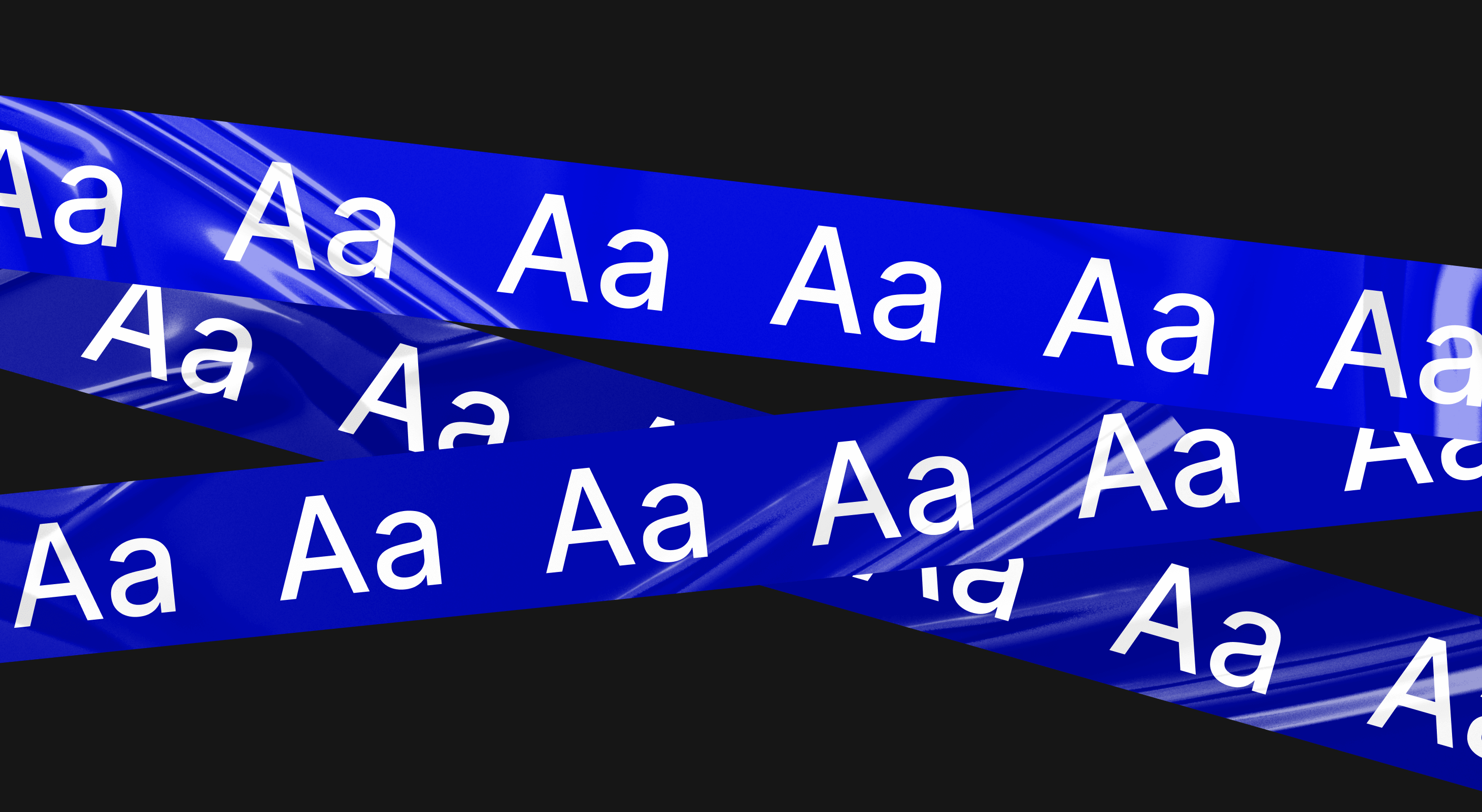
Как создать свой шрифт: инструкция
Если вы занимаетесь дизайном, но ни один из существующих шрифтов не подходит для вашего проекта, то создайте его сами. Это большой проект, но потраченные время и силы оправдают себя. В материале вместе с дизайнером Дарьей Токаревой разбираемся, как разработать и оцифровать свой шрифт.
Что нужно для создания шрифта
Чтобы сделать шрифт, нам нужно понимать, что же он из себя представляет. Крайне важно ориентироваться в базе типографики и разбираться в ее разновидностях. Это поможет определиться с целеполаганием: для чего создаем и где будем использовать.
Шрифт — набор графических знаков, который используется для отображения и восприятия текста. Каркас буквы — графема, которая служит базой для любого шрифта. По графеме мы понимаем, какая перед нами буква: к примеру, Н отличается от Л и О в любом шрифте и начертании.
Графема
Пример графем. Источник
Основные типы шрифтов:
1. Гротеск — шрифт без маленьких линий на концах штрихов, проще говоря, без засечек. Буквы состоят из прямых или закругленных линий и своим каркасом напоминают простые фигуры, такие как квадрат, прямоугольник, круг и другие.
1. Антиква — класс шрифтов с засечками, выступающими элементами. Существует давно, еще с эпохи Возрождения. Засечки лучше помогают читать большой массив текста.
1. Брусковый — шрифт с мощными прямоугольными засечками, похожими на бруски.
1. Акцидентный — простым языком, декоративный. Его функция — не набор текста, а акцент и привлечение внимания. Служит для заголовков и маленьких отрывков текста.
1. Рукописный — этот шрифт либо выполнен от руки, либо его имитирует. Наглядный пример: каллиграфия — пишут не отрывая перо, леттеринг — рисуют все буквы индивидуально под задумку композиции.
Область использования шрифта
Дальше нужно определить, где именно будет использоваться шрифт. Варианты следующие: в печати, на веб-сайте или в дизайне. Любой шрифт может использоваться в любой сфере, но вот некоторые рекомендации:
1. Шрифты с засечками — Serif. Используются в печатных материалах: книги, газеты и журналы. Засечки помогают тексту быть более читаемым. Основные примеры включают Times New Roman, Garamond и Georgia.
Шрифт Times New Roman
Пример шрифта с засечками. Источник
1. Шрифты без засечек — Sans Serif. Подходят для веб-дизайна и других цифровых медиа, там, где нужны легкость чтения и четкость. Такие буквы легче воспринимаются нами на экране. К классике примеров относятся Arial, Helvetica и Open Sans.
Шрифт Arial
Пример шрифта без засечек. Источник
1. Рукописные. Они подходят для творчества и создания уникальных дизайнов, однако с такими буквами стоит быть осторожными. Велика вероятность трудностей с прочтением. Такой тип шрифтов хорошо работает для различных заголовков, приглашений и логотипов. Примеры включают Lobster, Pacifico и Great Vibes.
Шрифт Lobster
Пример рукописного шрифта. Источник
1. Декоративные шрифты. Могут добавлять в проекты акцент, но также могут и затруднить чтение. Их лучше всего использовать для небольших объемов текста, в качестве «вишенки на торте». Примеры включают Balmoral, Zapfino и Burgues Script.
Шрифт Zapfino
Пример декоративного шрифта. Источник
Важно помнить, что выбор шрифта зависит от контекста и цели его использования. Например, для длинного текста лучше выбрать шрифт с засечками, а для веб-сайта — шрифт без засечек.
Как нарисовать свой шрифт
Начнем с создания первых набросков букв алфавита и цифр. Делаем это либо вручную, либо в графических редакторах для рисования. Помним о том, что каждая буква уникальна и должна легко прочитываться.
Вовсе не обязательно рисовать весь набор символов сразу. Для определения стилистических деталей и основных пропорций достаточно наметить несколько букв и цифр. При создании можно вдохновляться образами, различными темами или целью. Например, для начала определите, хотите ли сделать строгий шрифт или, наоборот, воздушный.
Для создания акциденции или декоративного варианта смотреть референсы можно, но не сразу. Лучше всего начать с косвенных референсов, а не смотреть сами шрифты. К косвенным референсам относятся образы, которые мы хотим адаптировать. Это может быть какой-то корабль, море, горы или птицы, в зависимости от задумки. К прямым референсам лучше обращаться после набрасывания первых идей.
Если же мы хотим сделать базовый строгий гротеск, то в этом случае нужно идти от обратного, учесть нюансы уже существующих шрифтов и понять, чем наш будет от них отличаться.
Создание первых букв
При создании шрифта на кириллице контрольными буквами обычно считают «о», «е», «м», «т» и «а», они позволяют оценить аспекты визуала и технических характеристик.
Обозначим высоту прописных, строчных, выносных элементов, а также базовую линию и ось. Важно учесть цельный ритм и настроение нашего шрифта, чтобы создаваемые буквы в итоге не «плясали».
3. Создание полноценного шрифта обычно занимает от нескольких недель до нескольких месяцев.
4. При создании шрифта используются специализированные программы, такие как FontLab, Glyphs, FontForge, а для начальной проработки иллюстраций букв подходят векторные программы — Adobe Illustrator и Figma.